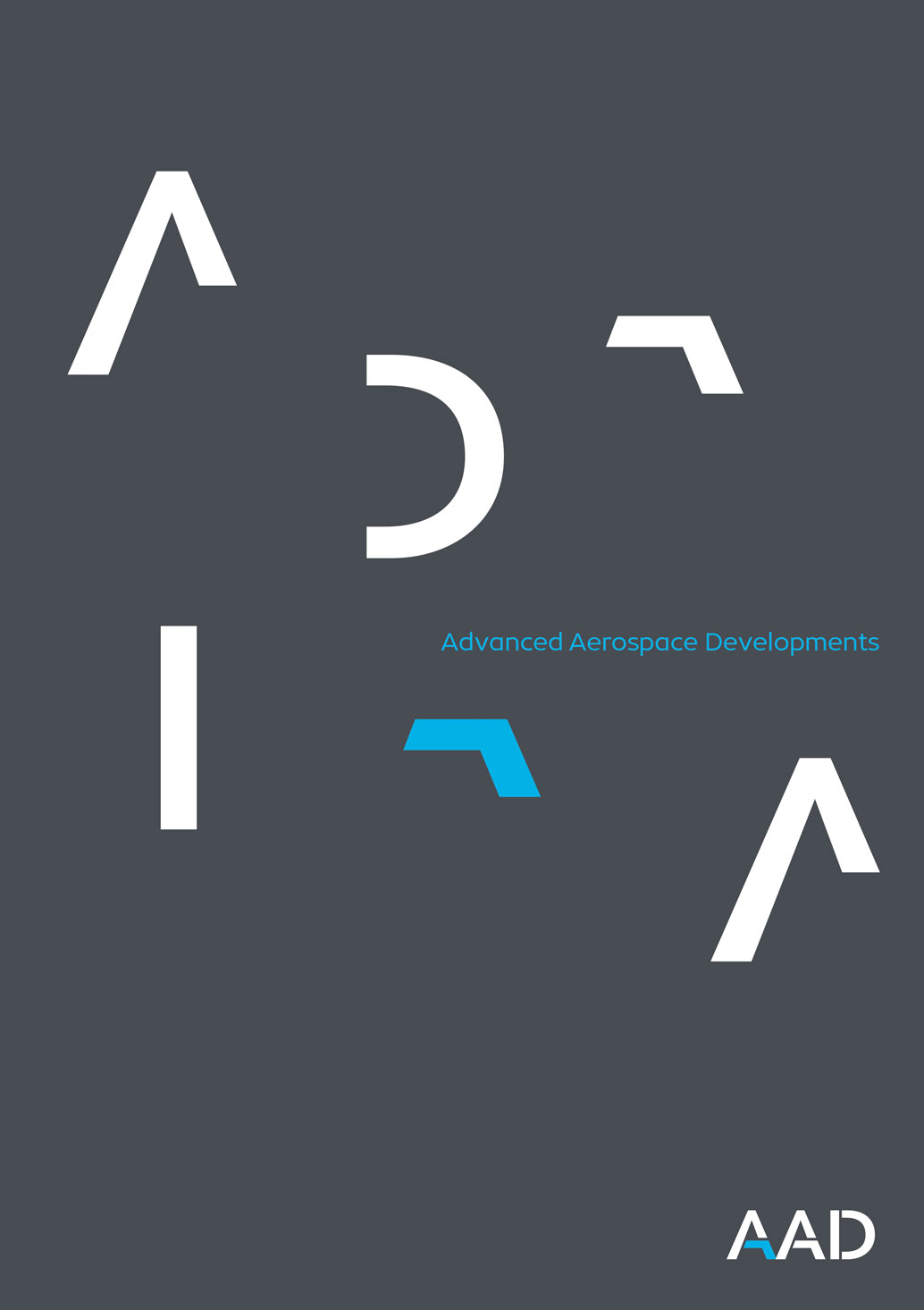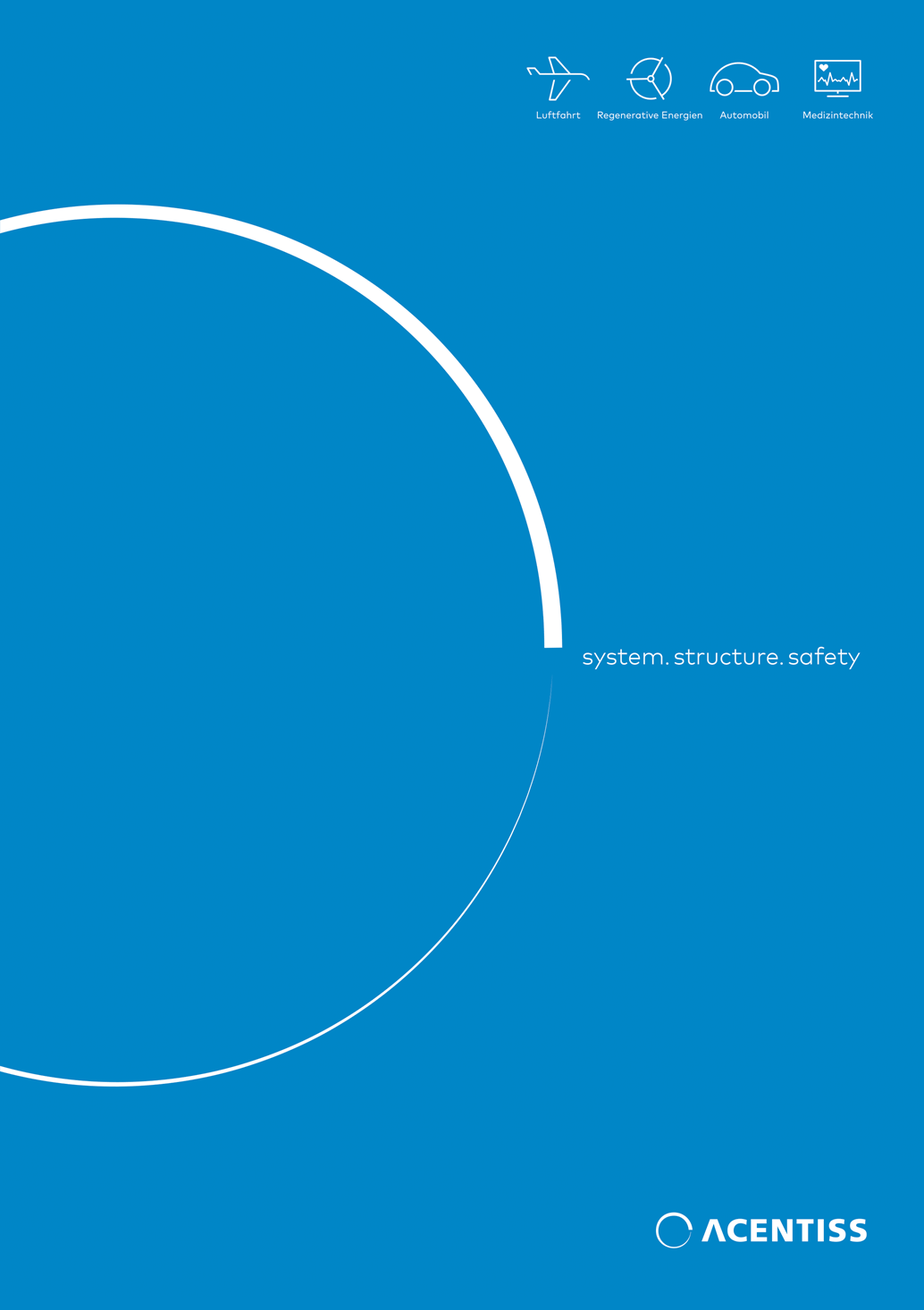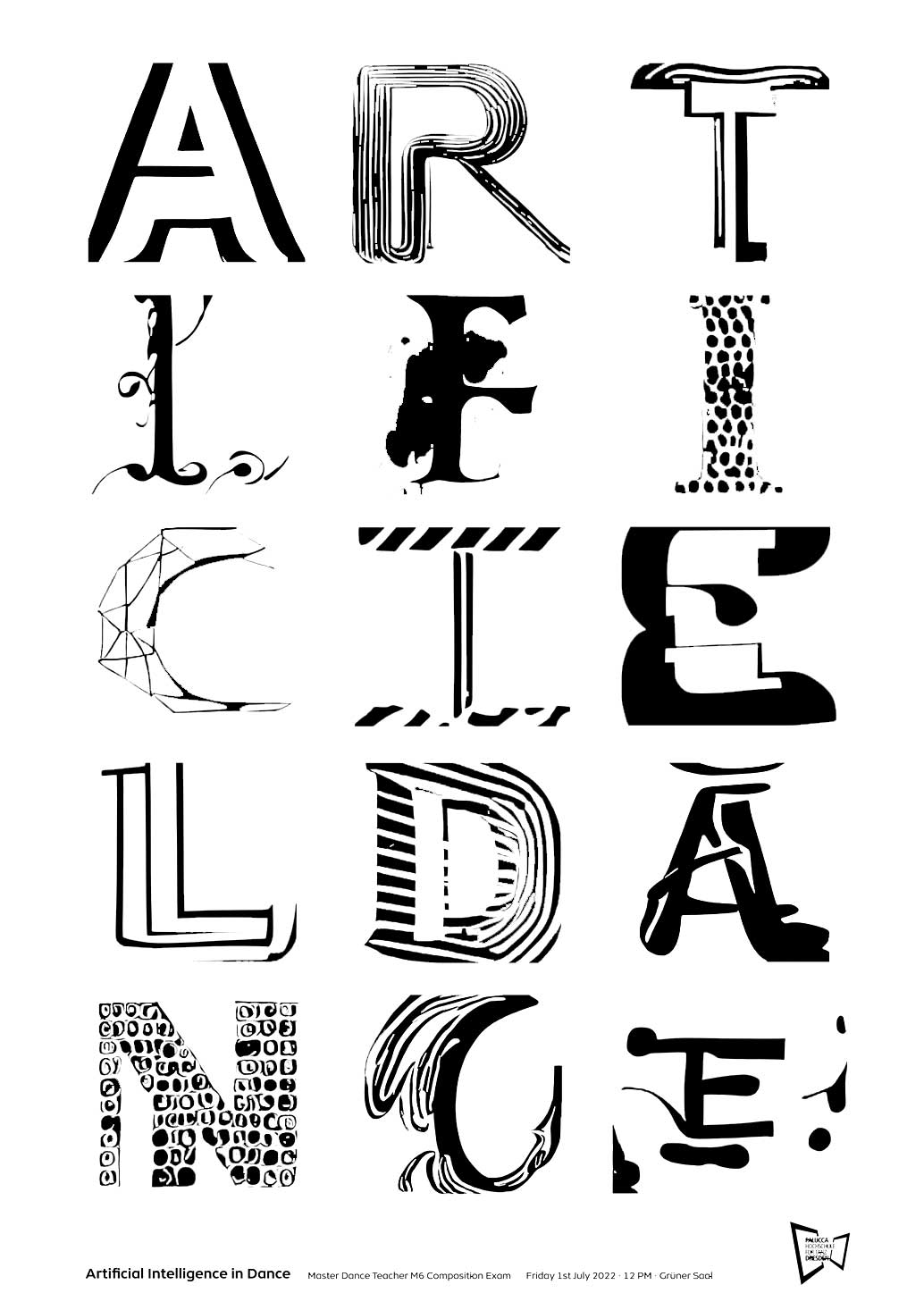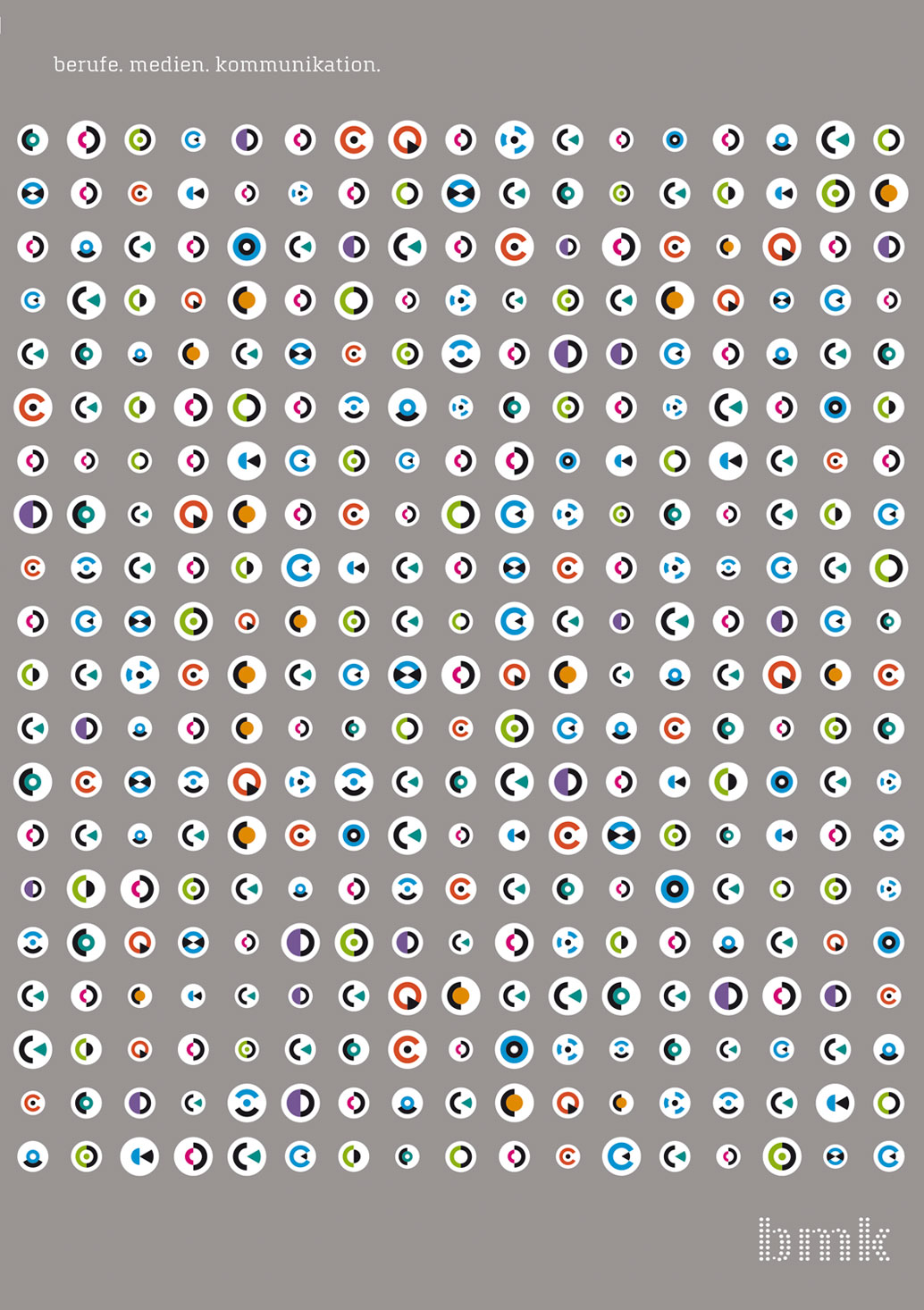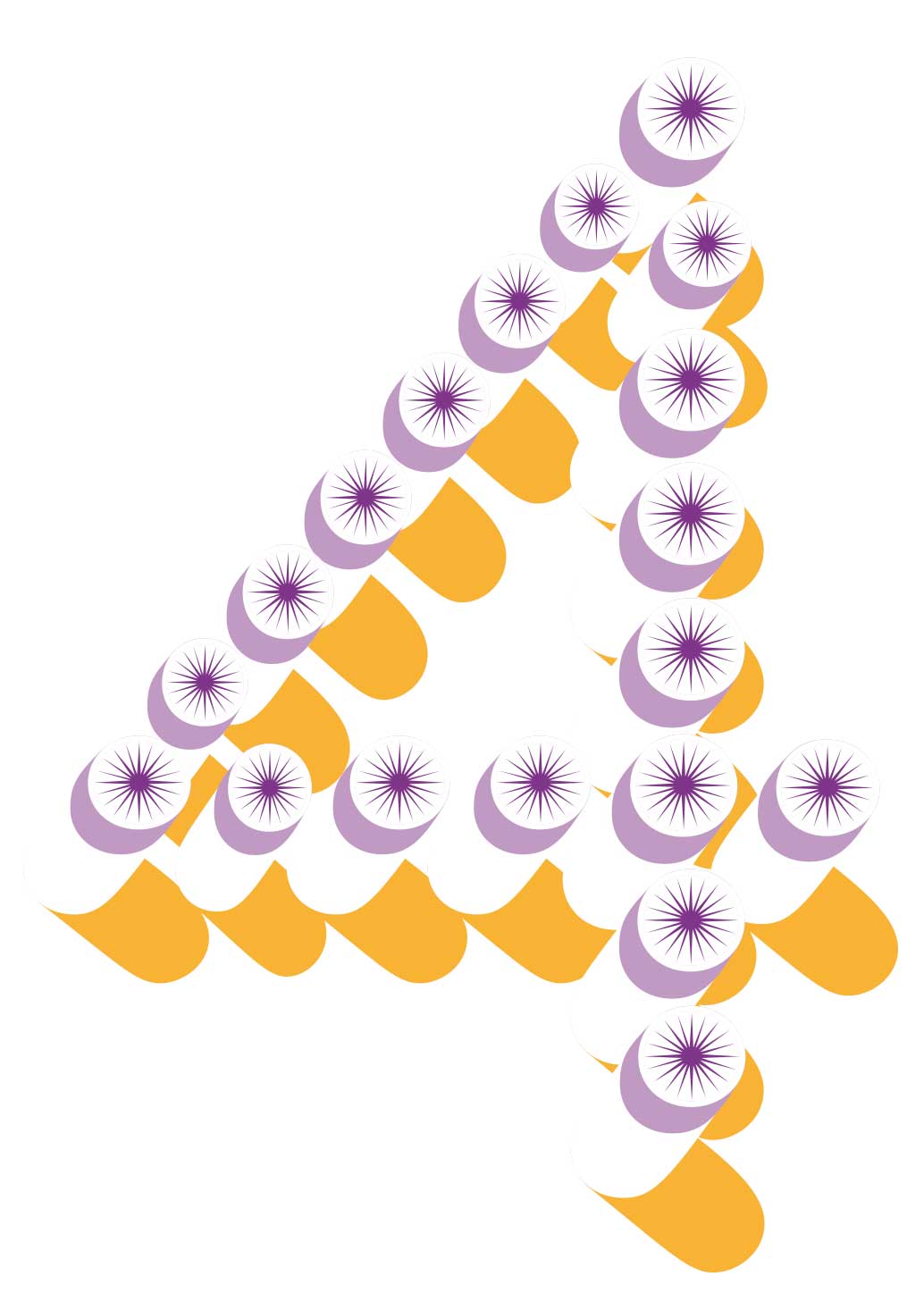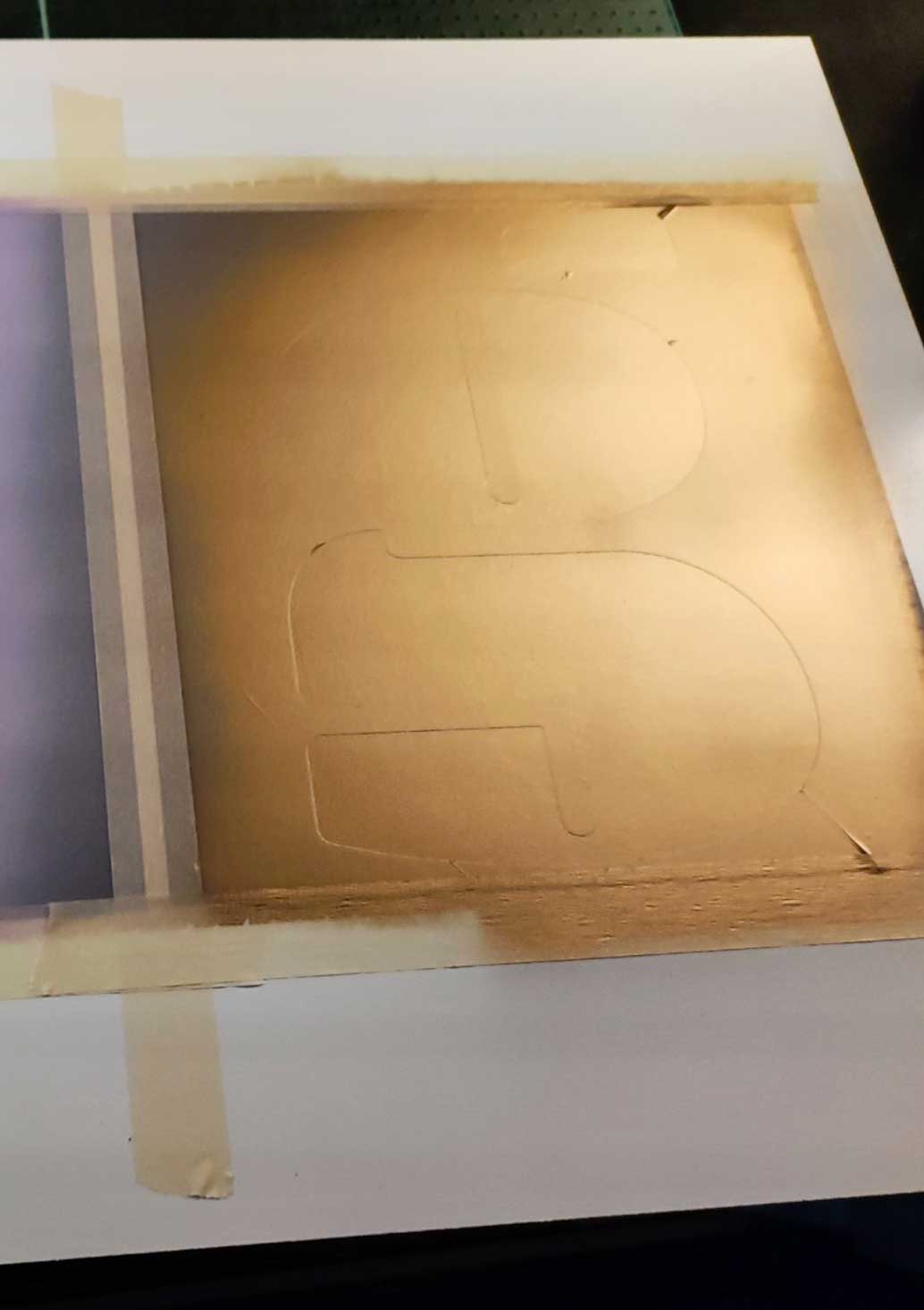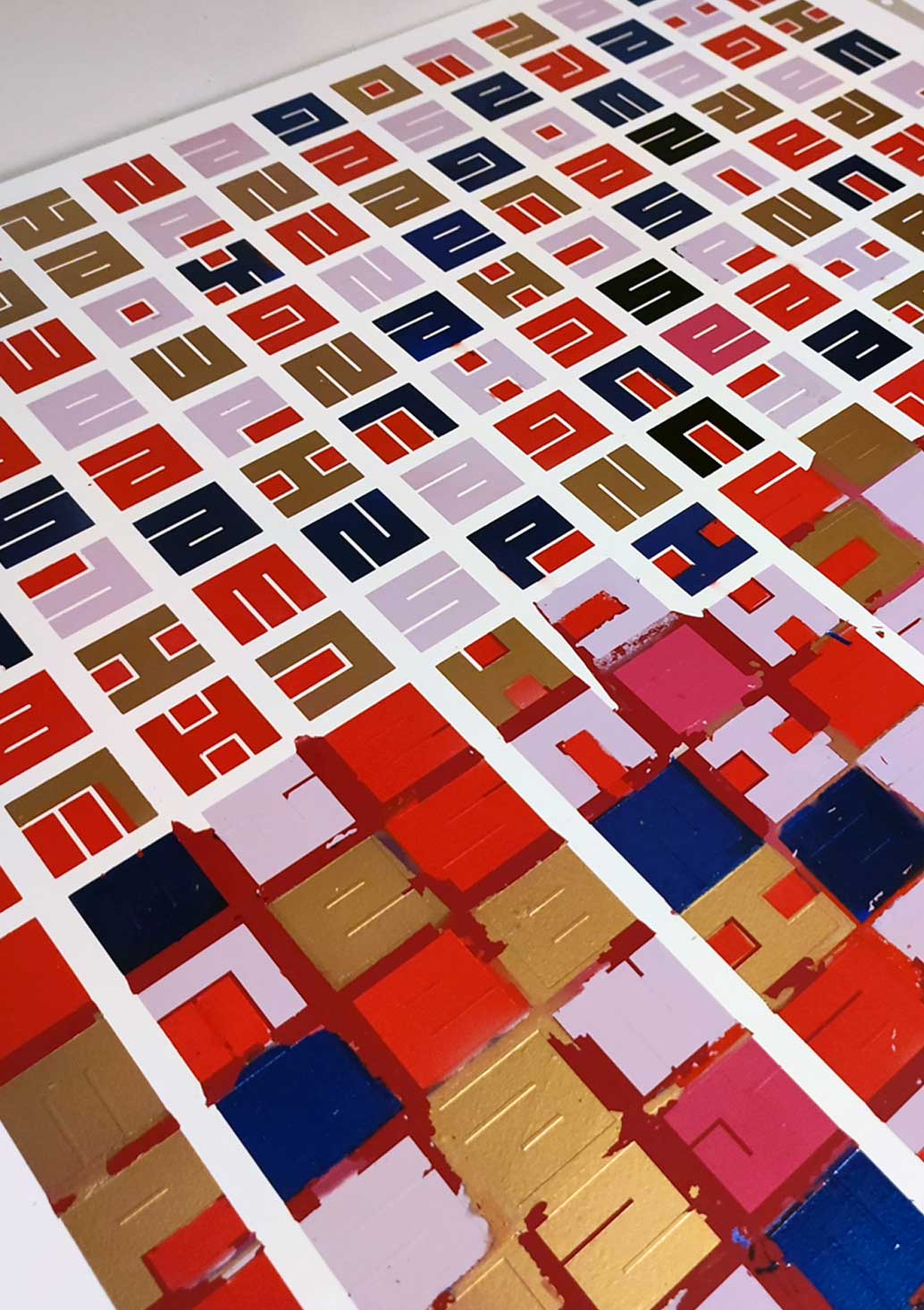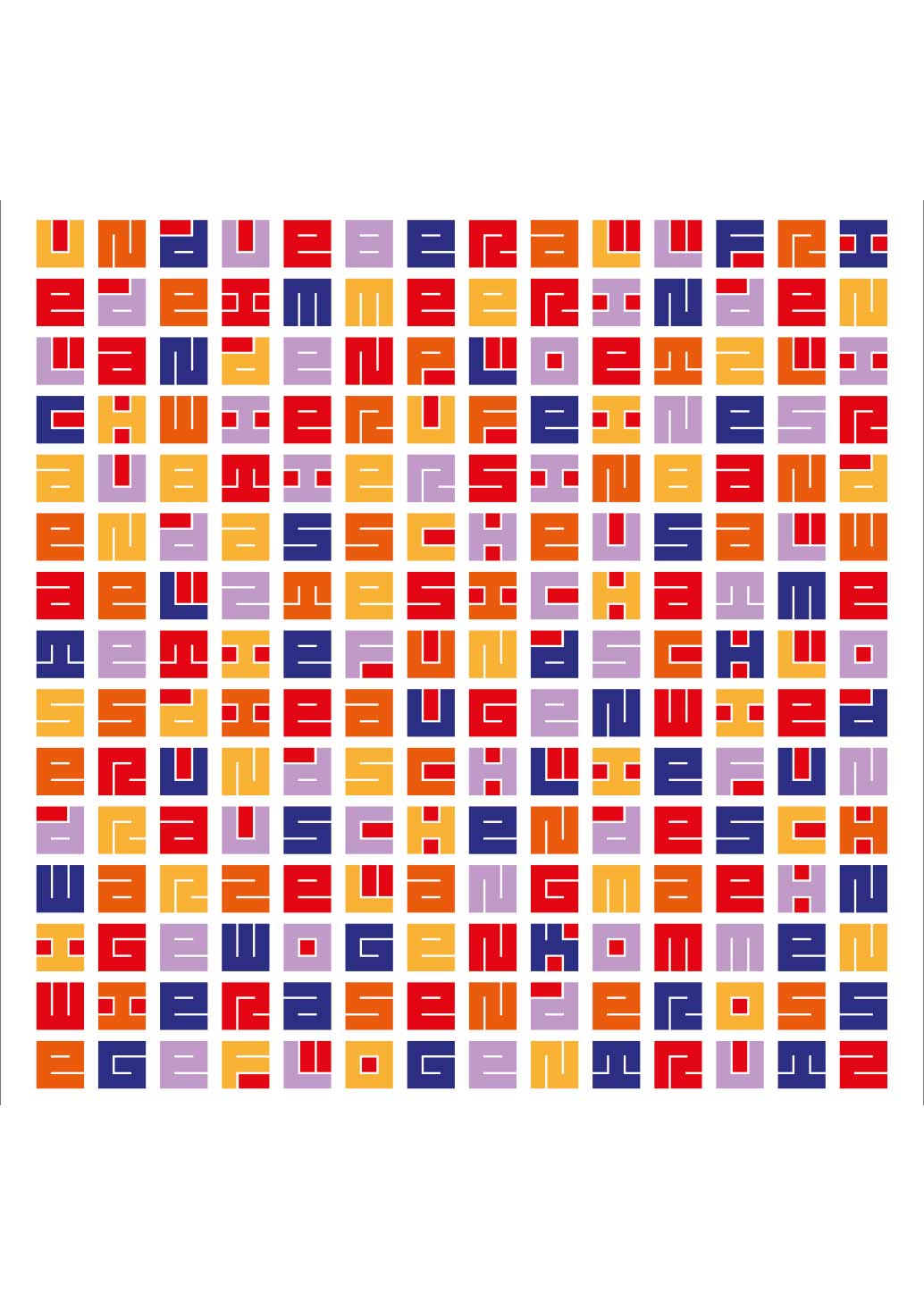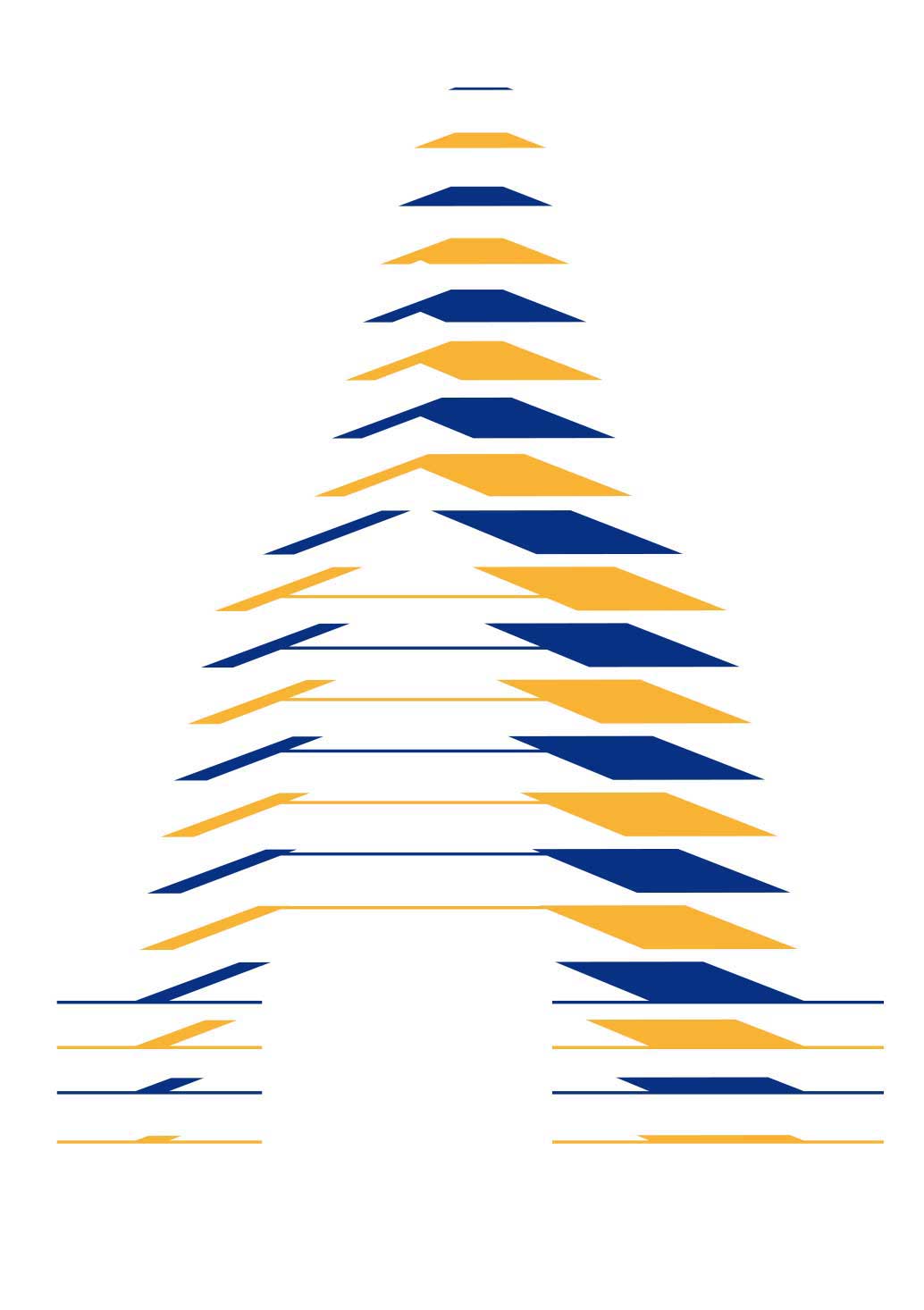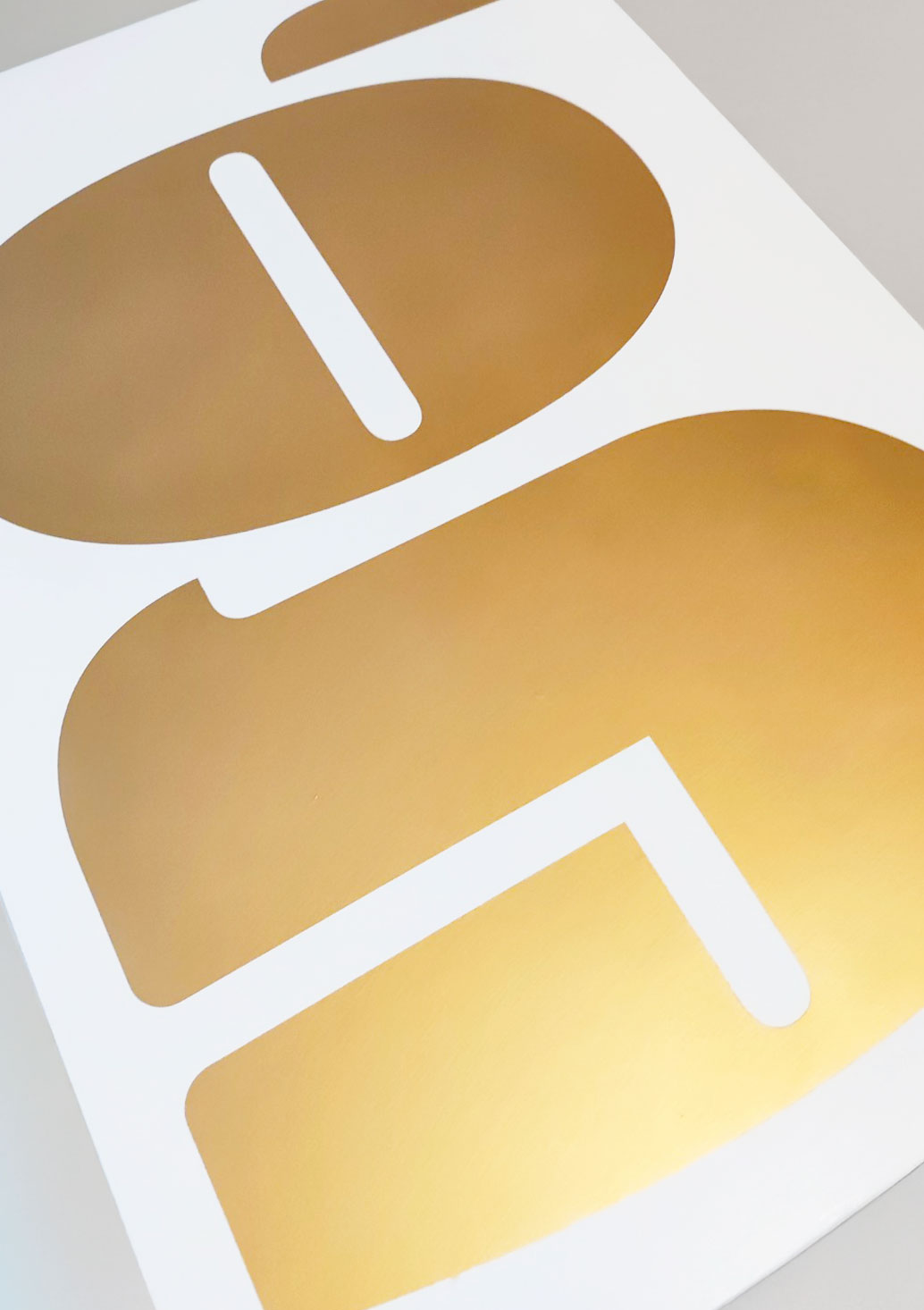
VITES – Visual Identity
VITES hat sich auf Produkte der Funktechnik für professionelle Einsatzgebiete spezialisiert. Zu den Kernkompetenzen gehört ine neu entwickelte Technologie für elektronische Funkstrahlsteuerung.
AAD – Visual Identity
AAD übernimmt die Entwicklung, Herstellung und den Vertrieb von Ausrüstung, Anbaukomponenten und Bauteilen für Luft- und Raumfahrzeuge, sowie für den allgemeinen Maschinenbau.
IAGB Teleport – Visual Identity
IABG Teleport steht für verlässliche, hochverfügbare und exakt auf die Kundenanforderungen zugeschnittene Kommunikationslösungen über Satellit und hat seinen Standort in München.
ACENTISS – Visual Identity
ACENTISS bietet umfassende Dienstleistungen im Bereich Entwicklung und Konstruktion von Leichtbaustrukturen in den Bereichen Luftfahrt, Automotive und Medizintechnik an.
INTIS – Visual Identity
INTIS hat sich auf integrierte Ingenieurdienstleistungen in den Bereichen Mobilität, Energie und Umwelt spezialisiert. Die dynamische induktive (drahtlose) Energieübertragung gehört zu den Kernkompetenzen des Unternehmens.
BMK – Visual Identity
»bmk« steht für »Berufliche Schule für Medien und Kommunikation« und entstand durch die Fusion von drei Schulen, die sich auf Ausbildungsgänge der Medienwirtschaft spezialisiert hat.
FONTADOR wurde im Zuge der Neustrukturierung und Positionierung mit der Entwicklung des neuen, gemeinsamen Corporate Designs beauftragt.
L’Quán – Visual Identity
Fünf Restaurants unter dem Namen »L’Quán« in Hamburg bieten moderne vietnamesische Küche.
L’Orient – Visual Identity
Vier Restaurants unter dem Namen »L’Orient« in Hamburg bieten libanesische Gastlichkeit und die Vielfalt orientalischer Köstlichkeiten.
»Laban« – Plakat
Die Typografie ist inspiriert von dem Notationssystem zur Aufzeichnung und Analyse menschlicher Bewegung von Rudolf Laban, das als eine Art Tanznotation verwendet wurde. Plakat für eine Tanzperformance von Elizabeth Ladrón de Guevara.
– Shortlist Communication Award 2021 / Poster
Atelier National de Recherche Typographique
Plakat im 7-farbigen Siebdruck für den ANRT Paris.
»Nomade« – Plakat
Plakat für eine Tanzperformance von Elizabeth Ladrón de Guevara.
»Vertigo« – Plakat
Das Ensemble Danza Urbana wurde 2005 von Elizabeth Ladrón de Guevara gegründet.
Es besteht aus verschiedenen Künstler/innen (Komponisten, TänzerInnen, Videokünstler, Schauspieler, Gast ChoreografInnen und anderen), die sich projektbezogen zusammenschließen.
Danza Urbana sucht die Interaktion verschiedener Kunstbereiche.
»Artificial Intelligence in Dance« – Plakat
Die unerwartete, mit KI erzeugte Typografie soll das Thema “Artificial Intelligence in Dance” vom Master Dance Teacher M6 Composition Exam an der Palucca Hochschule für Tanz visualisieren.
Typografische Monatsblätter
Ein 12-seitiger Beitrag zur Schriftentwicklung der Linotype Freytag und die Versuche konstruierter Alfabete am Bauhaus um 1925.
Briefmarken
Gestaltung von Postwertzeichen zu einem jeweils vorgegebenen Thema für das Bundesministerium der Finanzen.